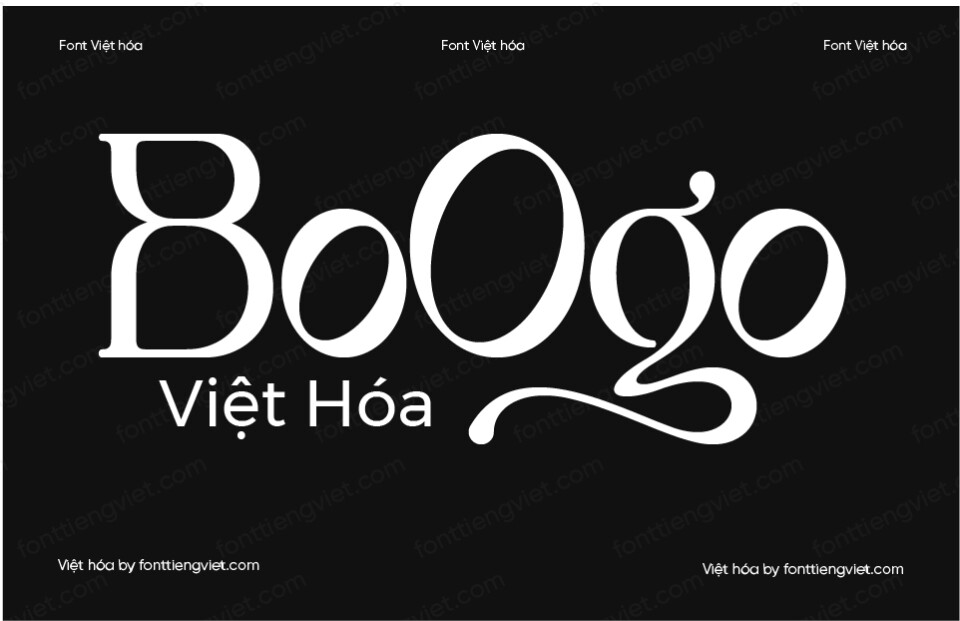
Font Việt hóa 1FTV VIP Boogo
Giới thiệu về bộ Font Việt hóa 1FTV VIP Boogo
Trong thế giới đồ họa hiện đại, việc lựa chọn một bộ Font Miễn Phí chất lượng luôn là ưu tiên hàng đầu của các bạn học sinh và thầy cô giáo. Font Việt hóa 1FTV VIP Boogo nổi lên như một giải pháp hoàn hảo nhờ phong cách thiết kế hiện đại, trẻ trung nhưng vẫn giữ được nét thanh lịch cần thiết. Đây là bộ phông chữ được tinh chỉnh kỹ lưỡng để phù hợp với bảng mã tiếng Việt, giúp người dùng không còn lo lắng về lỗi hiển thị dấu khi soạn thảo văn bản hay thiết kế slide bài giảng.
Đặc điểm nổi bật của font chữ
Bộ Font Việt hóa 1FTV VIP Boogo sở hữu các đường nét tròn trịa, tạo cảm giác thân thiện và dễ nhìn. Với cấu trúc chữ rõ ràng, bộ font này cực kỳ phù hợp cho các tiêu đề lớn, poster sự kiện trường học hoặc các trang trí sổ tay sáng tạo. Khả năng tương thích tốt trên nhiều phần mềm thiết kế như Photoshop, Canva hay PowerPoint giúp quy trình làm việc trở nên nhanh chóng và hiệu quả hơn bao giờ hết.
Cách ứng dụng Font Việt hóa 1FTV VIP Boogo hiệu quả
Sử dụng trong học tập và giảng dạy
Đối với môi trường giáo dục, việc sử dụng Font Việt hóa 1FTV VIP Boogo giúp các tài liệu học tập trở nên sinh động, thu hút sự chú ý của học sinh. Thầy cô có thể dùng font này để làm nổi bật các từ khóa quan trọng hoặc tiêu đề chương học. Ngoài ra, tính năng hiển thị sắc nét của nó cũng đảm bảo văn bản luôn dễ đọc ngay cả khi trình chiếu trên màn hình lớn hoặc in ấn trên giấy khổ nhỏ.
Kết luận về bộ phông chữ VIP Boogo